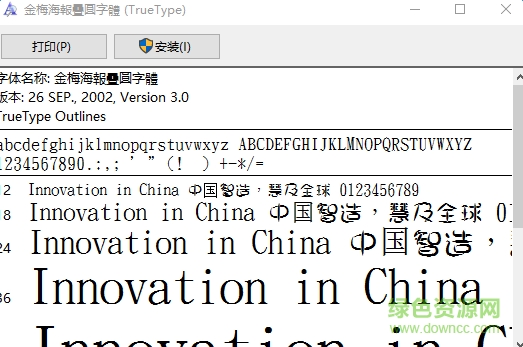
金梅海報疊圓
金梅海報疊圓字體是一款很不錯的電腦簡體字體,該字體寫出來的字活潑大方,而且越看越好看,也很實用,可以用于很多方面,歡迎有需要的朋友來綠色資源網(wǎng)下載。
金梅海報疊圓字體確實是一款很好用的電腦字體,用于書本印刷、藝術(shù)設(shè)計都是很不錯的,大家可以來綠色資源網(wǎng)免費下載。